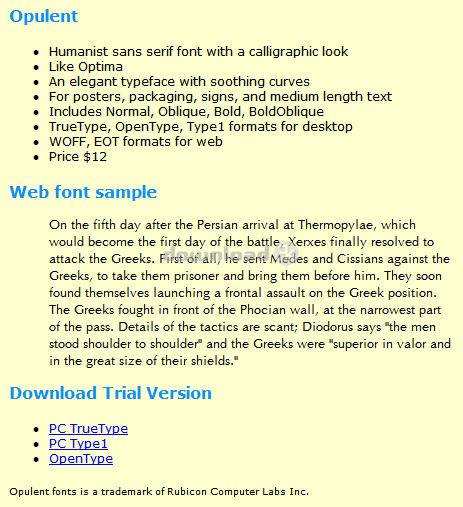
"Humanist sans serif font, calligraphic look"
Humanista sans serif con un aspecto caligráfico. Al igual que Optima. Un tipo de letra elegante, cálida, cuyas curvas son calmantes para el ojo. Un diseño para todo uso, ideal para los carteles, la publicidad, el envasado, los signos, y el texto de longitud media. Precisa y dio a entender, haciendo coincidir las métricas de fuente, juego de caracteres estándar, kerning pares. La calidad profesional de impresión de inyección de tinta, láser, cajista a 3500 dpi. Contrains una fuente de prueba. Los compradores reciben 4 variantes de la fuente de la siguiente manera: Normal, Oblicua, Negrita oblicua.Requisitos: No special requirements.